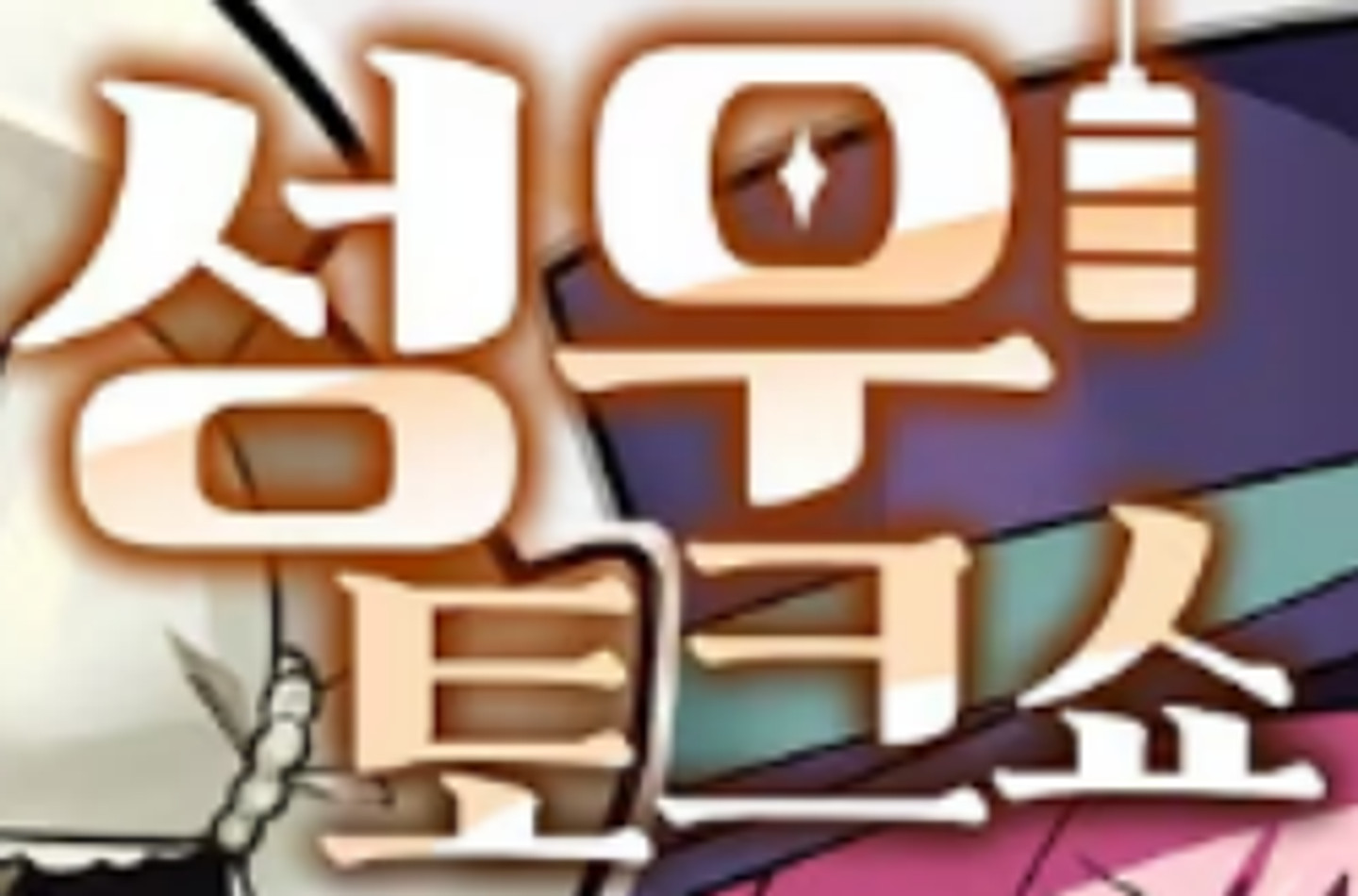
안녕하세요. 상업용 유튜브 썸네일 제목에 반복 사용할 한글 붓글씨 폰트를 찾고 있습니다. 첨부한 이미지왼쪽에 조선힙합채널처럼 자연스럽고 불규칙한 붓글씨 느낌을 원합니다. 획이 힘 있고 손으로 쓴 듯한 분위기이면서, 오른쪽 쇼츠 이미지처럼 글자가 굵고 통통하며 내부에 거친 긁힘·벗겨짐 질감이 있는 폰트를 찾고 있습니다. 특정 채널의 폰트를 그대로 복제하려는 것은 아니며, 비슷한 특징을 가진 다른 폰트를 찾고 싶습니다. ‘210 오늘은 Bold’도 확인했지만 제가 원하는 것보다 획이 다소 가늘고 날렵하게 느껴졌습니다. 이보다 굵고 힘 있는 붓글씨 또는 캘리그래피 폰트가 있다면 유료 폰트를 포함하여 추천 부탁드립니다. 추천 폰트에 대해서도 아래 내용을 함께 알고 싶습니다. 1. 유튜브 썸네일 및 영상에 상업적으로 사용할 수 있는지 2. 낱개로 영구 구매할 수 있는지 또는 구독이 필요한지 3. After Effects로 MOGRT 템플릿을 제작한 후 Premiere Pro에서 반복 사용해도 되는지 4. 외주 제작자와 작업할 경우 각자 별도의 폰트 이용권이 필요한지 5. 구독 종료 후 기존에 제작한 영상·썸네일을 계속 게시할 수 있는지 가능하다면 첨부 이미지와 가까운 후보를 여러 개 추천해주시면 감사하겠습니다.
솔폰트
Soul 커피브레이크, Soul 율곡, Soul 데스페라도 추천드립니다 솔폰트가 캘리그라피 폰트만 판매하는 곳이여서 둘러보시는 거 추천드려요 폰트는 설치형, 구독형이 있기 때문에 맘에 드는 폰트 발견하시면 확인이 필요할 것 같네용 4번 질문의 답변은 외주에서 제작 시 외주사에서 해당 폰트 라이센스가 있어야합니다 폰트 공유는 불가해요